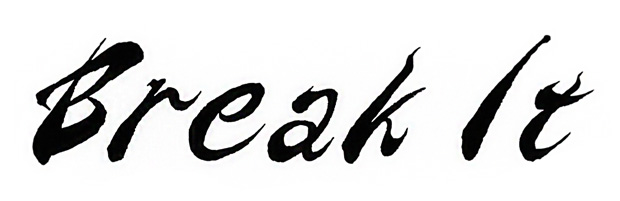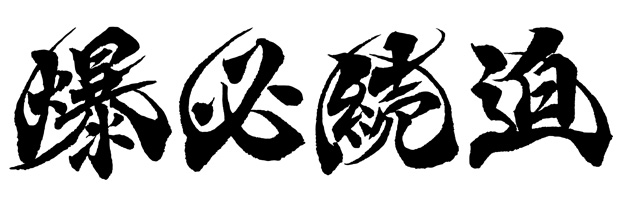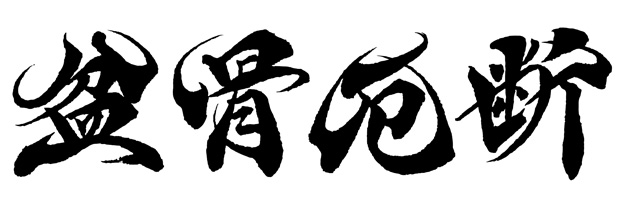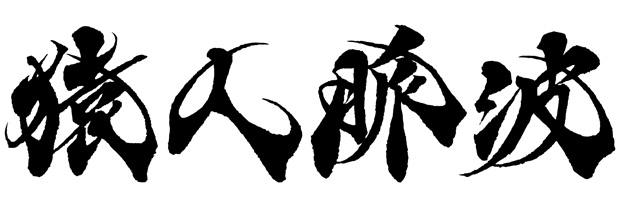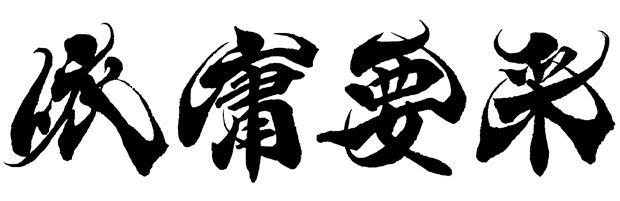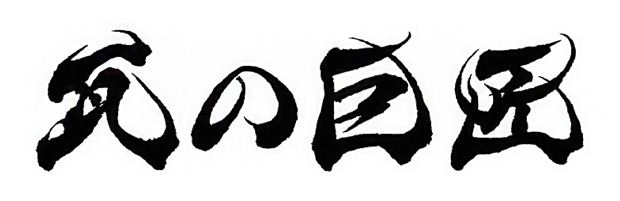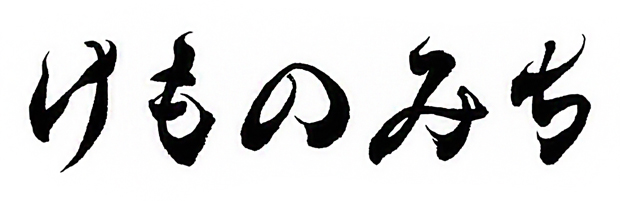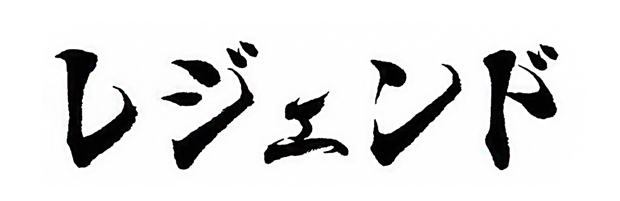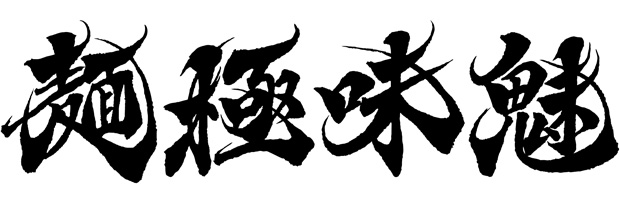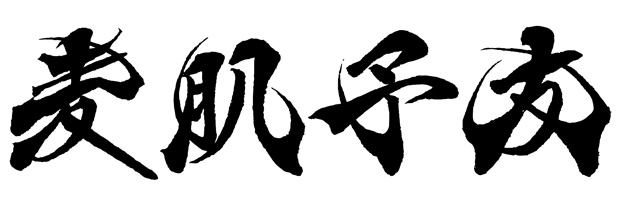
風の舞フォント見本
当ページでは和文フォント「風の舞」の書体見本を掲載しています。漢字・ひらがな・カタカナ・アルファベット・数字・記号の一部を公開しています。
毛筆フォント 風の舞による「竜猛破夜」。必殺技の名前にもご使用いただけます。
横書きの「熊野古道」
かっこいい風の舞フォント見本「仕事勝負」
墨の滲みを活かした「呪脅滅笛」。ゲームコンテンツの題字等にも風の舞フォントが映えることがあると思います。
筆文字デザイン「妖月鳴盟」。このフォントは同人誌の同好会名等にもお使い頂けます。
伸びやかで意気揚々とした「依庸要采」
「浪恋謡籠」の風の舞書体見本。書籍タイトル等、商用利用が可能です。
「麺極味魅」。麺が自慢の美味しいラーメン店店舗ロゴにも風の舞フォントは活躍することと思います。
「獣里虜旅」。旅行会社が企画するミステリーツアーのパンフレット等にもクレジット表記は必須ではなくご使用いただけます。
墨文字の「露克硫面」。WEBサイトのタイトルにも風の舞フォントはご利用可能です。
「猿人脈波」。この書体は力強く躍動的な映画タイトルにも合うと思うます。
「武貌和爵」。武芸に長けた和風漫画のロゴ等にもいかがでしょうか。
ロゴデザイン「盆骨厄断」。老若男女が楽しめる恐怖アニメのタイトルロゴ等にもお使い頂けます。
「柳盗悠了」。風の舞フォントは1文字単位でご購入頂けますので老若男女が楽しめる恐怖アニメのタイトルロゴ等、必要な時に必要な文字だけご注文頂けます。
美しさと高級感、そして躍動感等を兼ね備えたフォントの「麦肌予友」。化粧品のサンオイルの快活な商品パッケージロゴにもフォントが活きることと思います。
力強く奇抜な「栃可哺方」。この書体でYouTubeのサムネイル画像等にいかがでしょうか。
カッコいい文言の「爆必続迫」。このフォントは人気ゲーム会社の格闘ゲームのカッコいい必殺技等にも商用利用いただけます。
「郵文免乏」。イベントのポスターに掲載するロゴとして使用する際にも配置は自由に行っていただけます。
風に舞ったインパクトのある書体の「寮紋狭茂」。風の舞フォントが映画の題名にもお役に立てることがあると思います。
躍動的で力強く元気な毛筆英語フォント「Break It」。アルファベットの大文字と小文字の組み合わせのサンプル画像です。
アルファベットの大文字の風の舞フォント「PIERRE」。月山書体 風の舞フォントでは欧文もタイピング出来ます。
アルファベットの大文字と記号の組み合わせの「FIGHT!」。風の舞フォントのアルファベットも力強く活気があります。
漢字とひらがなの組み合わせの「島人ぬ宝」。風の舞フォントの筆文字はキャッチフレーズ、社是、座右の銘、社訓、キャッチコピー等にも1文字単位でご購入頂けます。
漢字仮名交じりの「瓦の巨匠」。風の舞書体は太字フォントで人気です。
ひらがなのフォント文字見本「かざぐるま」。この書体で会社の看板や名刺、チラシ、フライヤー、ホームページ等の商用利用が可能です。
ひらがなの構成の横書き画像「けものみち」。納品時の色は墨色(黒)の筆文字ですが、広告代理店、デザイン会社、グラフィックデザイナー様等がカラーにして使用することができます。
お菓子の商品名「おせんべい」。商品のパッケージ、ラベル、包装紙、シール、ステッカー等、風の舞フォントの毛筆書体は幅広くご利用頂けます。
居酒屋のお酒のつまみのメニュー「するめいか」。風の舞フォントは飲食店のお酒の肴、あて、メニューにも使用できます。
ひらがなの月山書体 風の舞フォント見本「さとのあき」。
筆文字の大小、太細いの変化のある「なりこまや」の見本。外国人観光客をターゲットにした高級旅館の看板にもこのフォントをお役立てください。
植物の総称「ジャスミン」。最高級茶葉を取り扱うお茶専門店の商品パッケージにも合うかと思います。
カタカナの筆文字デザイン「レジェンド」。
躍動的な数字の毛筆デザイン「24680」。
風の舞フォントの記号の見本「『』、。?!〆+」。
【竜猛破夜】
2024年の干支をイメージして『竜』を使用しました。
【熊野古道】
この風の舞フォントの書体なら地名に使用しても不自然ではないと思われます。
【仕事勝負】
仕事は元気があった方が能率が良いと思います。このフォントの書体なら合うかと思います。
【呪脅滅笛】
笛の音は遠くへ高く響いていきます。この様に色々な楽器の名前にこの書体を用いるのはいかがでしょうか。
【妖月鳴盟】
風の舞フォントの『月』は実際の月の形ではありませんが、月の美しさを月の文字に変えて表現しました。
【依庸要采】
「依」のように三角の構成は安定をもたらし、4文字の中に1文字でもあると雰囲気が変わります。
【浪恋謡籠】
1文字の中にも起筆の変化が筆文字らしさを強調させることができます。
【麺極味魅】
波磔の長さは風の強さを表現します。
【獣里虜旅】
旅をする時、元気である方がより一層楽しいものです。この書体は躍動感、力強さ、高級感、美しさに限らず楽しささえも表現するよう試みました。
【露克硫面】
どんなスポーツでも躍動感があります。この書体はスポーツ用品の商品ロゴやフィットネスクラブの企業ロゴ等にも合うと思います。
【猿人脈波】
「脈」や「波」のように旁(つくり)の上に偏(へん)を乗せるのも筆文字デザインならではの試みです。この部分にも筆文字デザインの良さを活かしました。ありとあらゆる分野に、この風の舞フォントを使用して頂きたいと思っております。
【武貌和爵】
よく日本の漢字を外国人が好むと言われます。宣伝目的での文字にこの書体の文字を用いてみてはいかがでしょうか。
【盆骨厄断】
劇団の演目に使用するタイトル文字として人目を惹くこの書体が活きてくると思います。
【柳盗悠了】
人はゲームを好みます。どこか遊び心があるこのフォントはいかがでしょうか。
【麦肌予友】
右払いに変化をもたらしたことで、風の舞フォント独自の魅力の1つにもなっております。
【栃可哺方】
看板にとって大事なのは、印象に残るインパクトの強い文字だと思います。他に類をみない風舞書®の書体をお役立て頂ければ幸いです。
【爆必続迫】
飛んだり跳ねたり体を動かすゲーム等は、躍動感表現が合います。風の舞フォントの書体は全て躍動感を表現することにしています。
【郵文免乏】
郵便物などが届くと、心待ちにしていた喜びがあります。この書体は体の動きに限らず心の動きを表現する力があります。
【寮紋狭茂】
このフォントは1文字1文字を丁寧に、個性的なロゴにも使えるように配慮して制作しました。
【Break It】
アルファベットとはいえ毛筆には書き手の個性を活かした方が良いと考え、漢字の古典を勉強した結果出来上がったアルファベットの見本です。
【PIERRE】
日本人の名前をアルファベットで書く場合もあります。やはり筆文字の線の太さ等変化させデザイン性が高い方が魅力があると思います。このフォントは名刺や表札にもご使用いただけます。
【FIGHT!】
自分に対しても他人に対しても、元気を求める場合どこか躍動感を求めているのではないでしょうか。
【島人ぬ宝】
漢字とかなを同じ書体で書きました。違和感がなく、見る人に自然に溶け込んでいるかと思います。
【瓦の巨匠】
食品に限らず建築物の宣伝にも、どっしりと力強く明るさを兼ね備えた書体としてご活用いただければと思います。
【かざぐるま】
ひらがなに対しても躍動感を風の舞フォントで表現しています。風車のように、動くものの宣伝にこの書体はいかがでしょうか。
【けものみち】
近年、益々電子書籍が普及し売上にはタイトルの文字も影響すると思います。様々なジャンルの本のタイトルに、一風変わったこのフォント文字を取り入れて見てはいかがでしょうか。
【おせんべい】
おせんべい等の食品パッケージには、見るからに汚い文字では味が悪そうに感じてしまいます。爽やかさがあり元気そうなこの書体は、パッケージや包装紙、ラベル等にもご利用いただけます。
【するめいか】
どこか奥深い味のする、するめいか等にもこの書体が顧客を呼ぶ力がありそうです。
【さとのあき】
この風の舞フォントは感情の表現として色々兼ね備えておりますが、このフレーズのように哀愁を帯びた表現にも使っていただけたらと思います。
【なりこまや】
看板には、全て平仮名の文字を使うこともあります。そんな時、個性的な文字は人目を惹きます。
【ジャスミン】
人は、香りといえば甘さや爽やかさ等「良い香り」を求めます。その香りが風によって運ばれてきたとき、何の香りか確かめようとします。この文字は風に乗って漂ってくるジャスミンの花の甘く爽やかな香りをイメージしました。
【レジェンド】
レジェンドという言葉の意味を表現するのに、昔からあった一般的に使われるフォント文字よりも特別な表現を持つ風の舞フォントが合うかと思います。
【24680】
算用数字はデザインすればする程、読みにくくなる傾向にあります。必要最小限度のデザインに抑えました。この算用数字は、漢字・かな・アルファベット・カタカナにも合うように制作しました。
【『』、。?!〆+】
記号は、機械化したフォントの方が毛筆フォントよりも読みやすさの点では遥かに優れています。筆で書いたとはっきり分かる記号は多少読みずらくとも人の手の温もりを感じるものです。